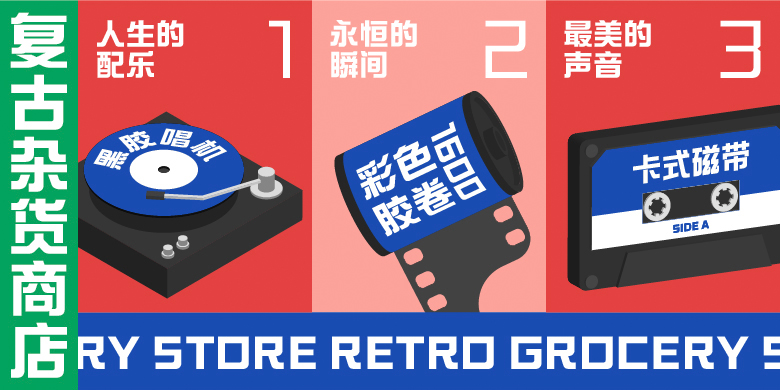
方正新综艺黑 详情页
方正新综艺黑
综艺体由郭炳权老师创作于上世纪70年代,与英文字体“Helvetica”有异曲同工之妙,至今仍受大众所喜欢,新综艺黑沿用综艺体部分特征,结合更舒适的视觉效果对相关笔画进行了再度的修改使其整体感觉更加的舒畅灵动,整体字形端正平稳,结构简洁大方,新综艺黑共有11个字重,更加的适合运用于各类场合及品牌宣传推广,是一款实用的字体。